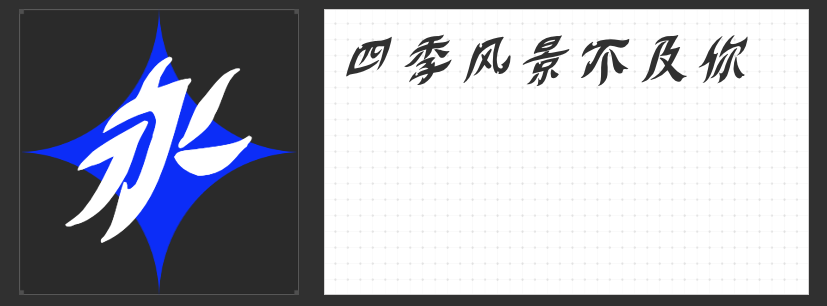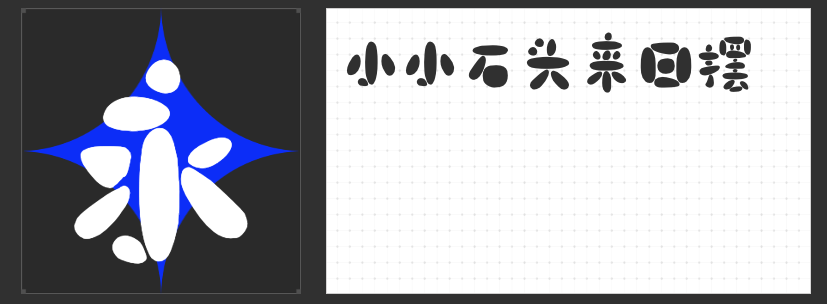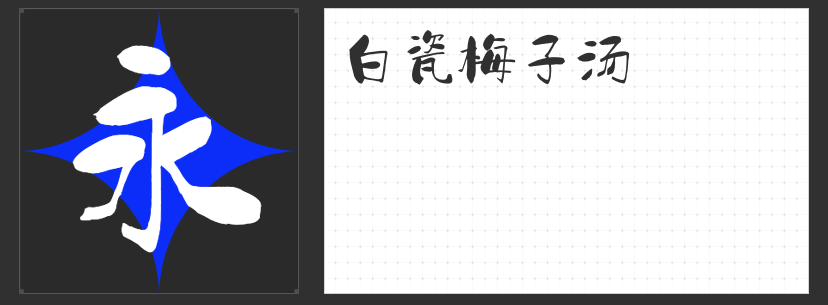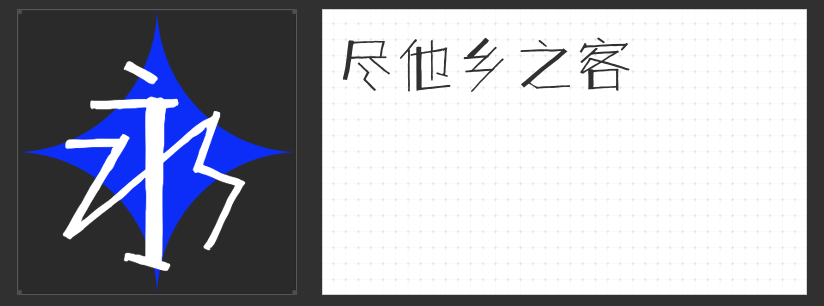
探索视觉奇境:形状独特的字体推荐
在字体设计的广阔天地里,总有一些形状奇特的字体,它们如同奇幻世界的钥匙,解锁了视觉表达的新维度。今天,就让我为您推荐四款令人眼前一亮的奇特字体,它们各自拥有独特的魅力,定能为您的设计作品增添无限创意与个性。
第一款:万人字造李峰连山若体 细体
这款字体仿佛是从遥远星系飘来的文字,每一笔一划都充满了未知的神秘感。其独特的星形元素融入笔画之中,让人仿佛置身于浩瀚的宇宙之中,探索未知的奥秘。适合用于科幻、未来感强的设计项目,如科幻电影海报、太空主题展览等。
第二款:万人字造一骏炎黄图腾体 大粗
万人字造一骏炎黄图腾体 大粗以其扭曲变形的笔画著称,仿佛是从梦境中抽离出的文字碎片,既诡异又迷人。这种字体适合营造梦幻、超现实的氛围,适合用于艺术展览、音乐节海报等追求独特视觉体验的场景。
第三款:万人字造昊仔体 大粗
万人字造昊仔体 大粗不仅赋予了文字更强的视觉冲击力,更展现出一种力量感与霸气,让人一眼难忘。无论是用于品牌标识、广告标语还是海报设计,万人字造昊仔体 大粗都能以其独特的风格和强烈的视觉效果,瞬间抓住观者的眼球。
第四款:万人字造趣石简 特粗
与前三款不同,万人字造趣石简 特粗以其模拟石头的笔画为特色,每一笔都仿佛是大自然中生长,充满了生命力和动感。这款字体适合用于环保、自然主题的设计项目,如生态公园宣传、绿色生活倡导等。
这四款形状奇怪的字体,每一款都拥有其独特的风格和适用场景。它们不仅能够为设计作品增添视觉冲击力,更能通过独特的字体语言,传达出作品背后的深层含义和情感。无论是追求科幻感的未来设计,还是渴望自然和谐的生态表达,这些奇特字体都能成为您设计路上的得力助手。